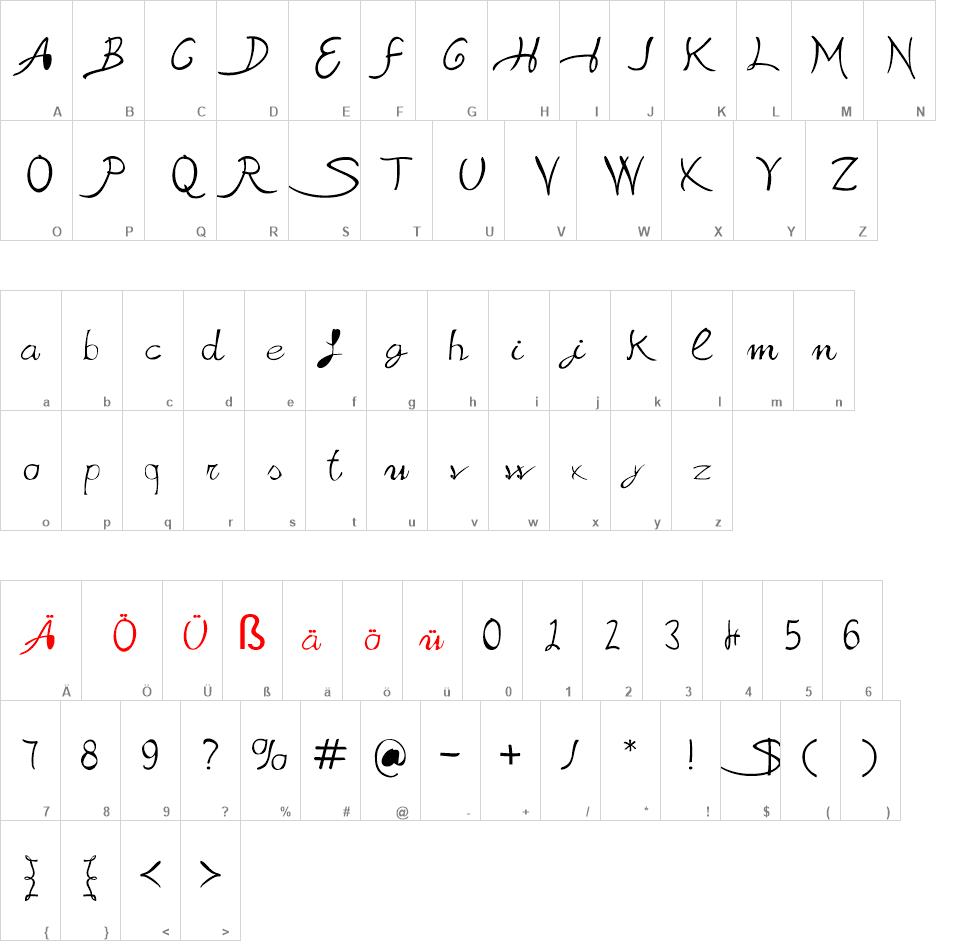
Sabrina
Sabrina font
Sabrina
SABRINA Schriftart: direkt aus dem Besten Film von Billy Wilder, mit AUDREY HEPBURN und HUMPHREY BOGART,
die Originalschrift für alle Liebhaber.